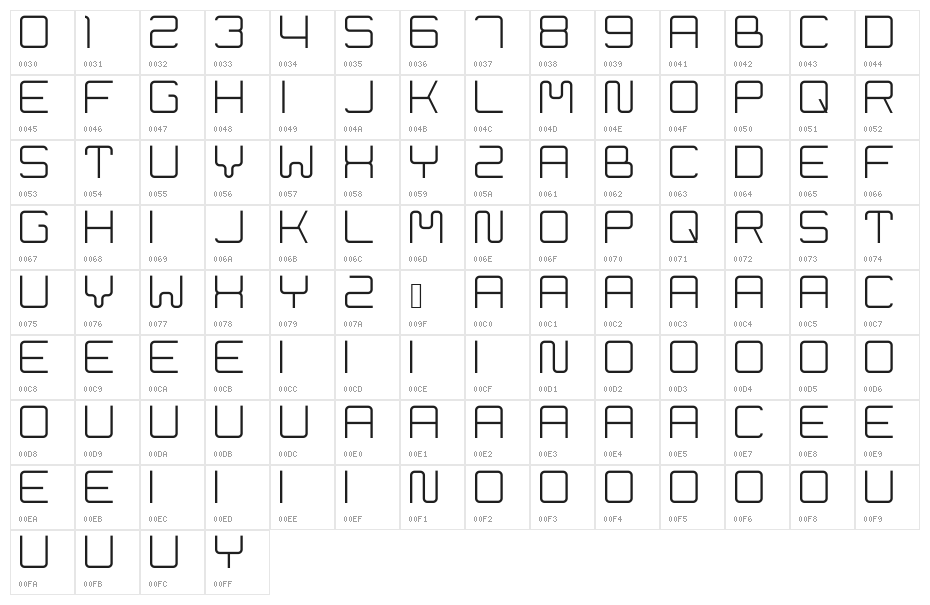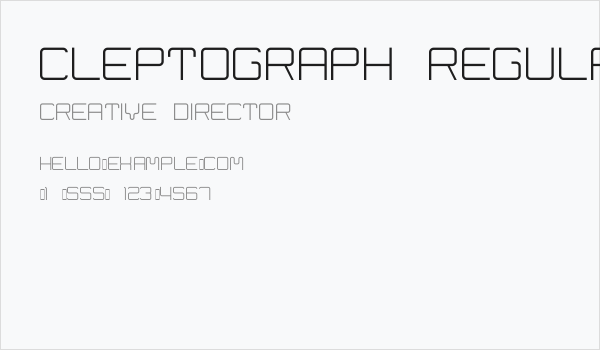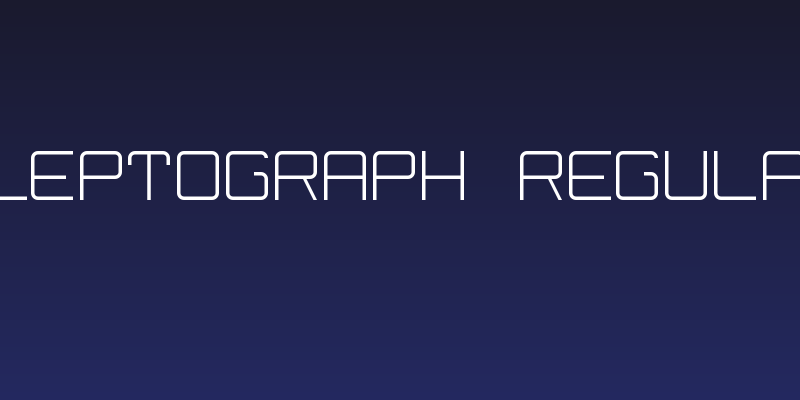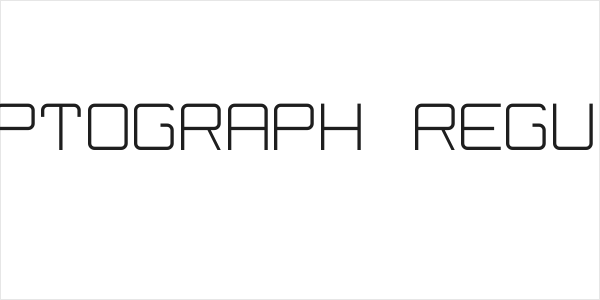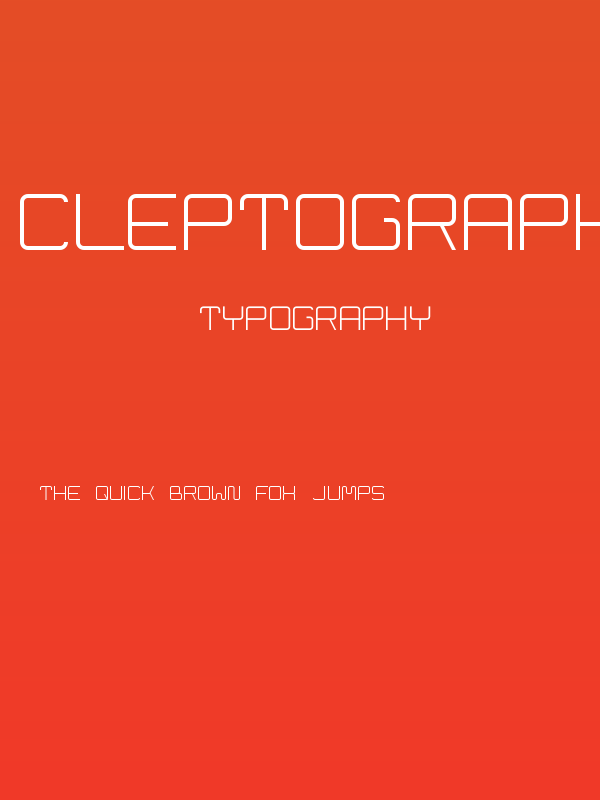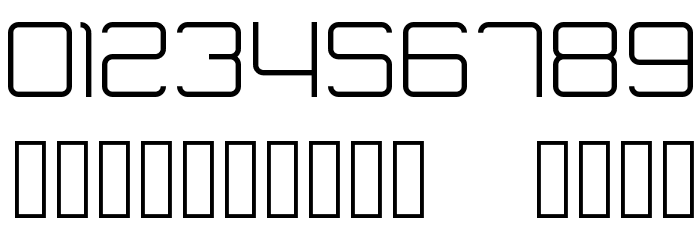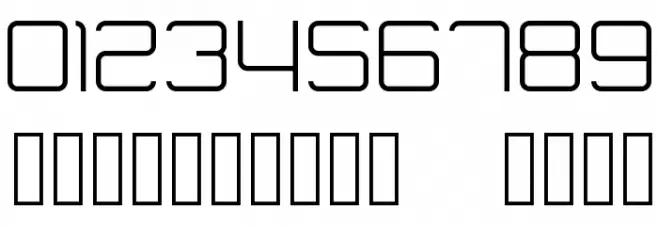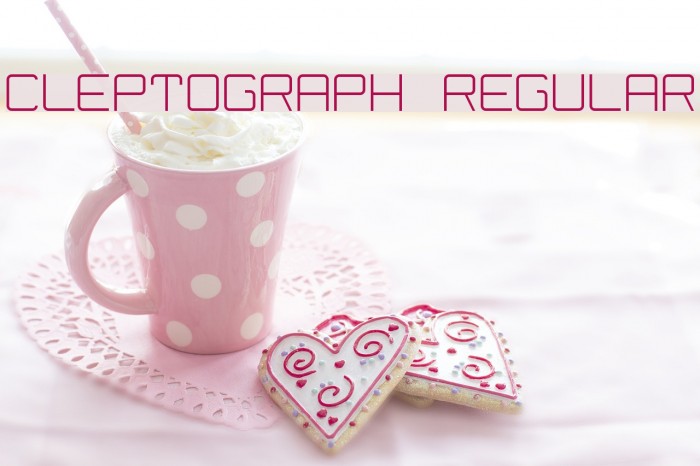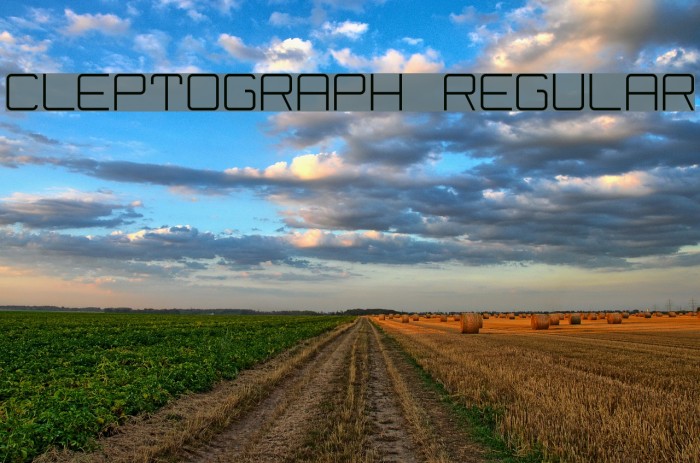
Cleptograph Regular Font
✎ Futuristic
| حالة الاستخدام | Logos, Headlines, Digital interfaces |
| مشاريع مقترحة | Ideal for technology branding, modern posters, digital interfaces, and futuristic designs. |